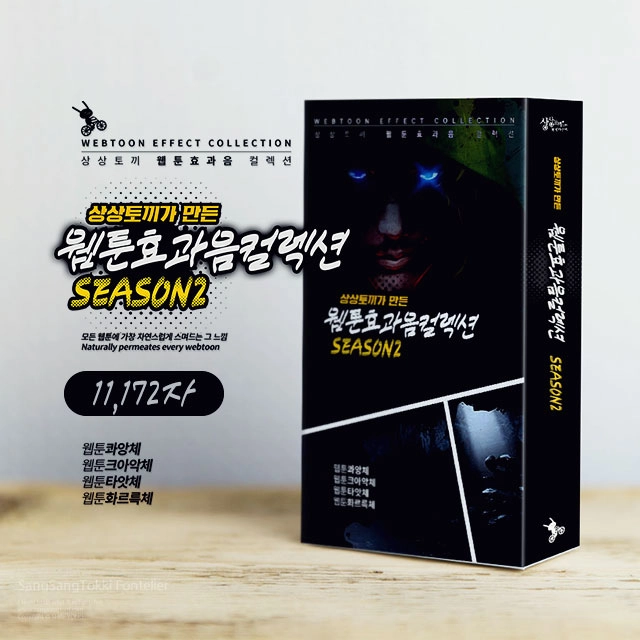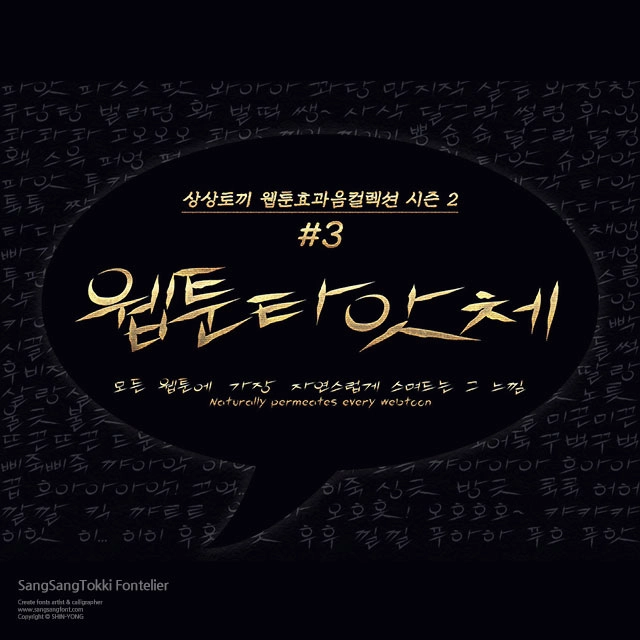
웹툰효과음컬렉션 시즌2, 4종
상상토끼의 웹툰 작가들을 위한 효과음 폰트 패키지 웹툰효과음컬렉션 시즌2, 4종
한글 11,172자 / 영문 52자 / 약물 84자
웹툰콰앙체 1종
웹툰크아악체 1종
웹툰타앗체 1종
웹툰화르륵체 1종
| <웹툰효과음컬렉션>은 웹툰 작가들의 효과음 폰트 선택 고민을 조금이나마 덜어주기 위한 목적으로 기획되었습니다. 효과음 작업시에 상황에 맞는 개성있는 폰트들을 선택하여 사용할 수 있습니다. |
| <웹툰효과음컬렉션> 시즌2는 역동적인 장면 연출에 잘 어울리는 웹툰콰앙체, 좀비물이나 공포/스릴러물에 잘 어울리는 웹툰크아악체, 타격감 있는 액션/느와르물에 찰떡궁합인 웹툰타앗체 그리고 독특한 질감을 가진 웹툰화르륵체까지 총 4종으로 구성되어 있습니다. |
#1 웹툰콰앙체 날카로운 획이 수직으로 길쭉하게 뻗어서 시원한 느낌을 주는 웹툰콰앙체입니다. 임팩트 있는 장면이 많은 스포츠물이나 스피디한 액션물등에 잘 어울립니다.
#2 웹툰크아악체 손으로 막 갈겨 쓴 듯한 거친 획들로 이루어진 웹툰크아악체입니다. 제목에서 알 수 있듯이 비명 소리에 잘 어울리는 폰트로 공포물이나 좀비/스릴러물의 효과음 표현에 좋습니다. 또한, 효과음뿐만이 아니라 거친 대사나 욕설, 소리지르는 문장으로 사용하는데도 불편함이 없습니다.
#3 웹툰타앗체 동작이 크고 역동적인 장면에 어울리는 웹툰콰앙체와 달리 섬세하고 예리한 액션 연출에 좋은 웹툰타앗체입니다. 어둡고 음침한 뒷골목 주먹들의 싸움이나 킬러물/느와르물의 날카로운 액션 연출이 필요할때 선택한다면 더할나위 없이 잘 어울리는 폰트입니다.
#4 웹툰화르륵체 불꽃이 이글거리는 모습을 형상화한 웹툰화르륵체입니다. 웹툰화르륵체는 다른 폰트들과 달리 그 형태가 워낙 명확하기 때문에 사용 범위가 제한적일 수도 있습니다. 하지만 불과 관련한 상황 연출이나 분노로 이글거리는 캐릭터의 감정 묘사등에 잘 활용한다면 멋진 장면을 얻을 수 있을 것입니다.
| <웹툰효과음컬렉션>은 한글 11,172자 / 영문 56자 / 약물 84자를 지원하기 때문에 짧은 단어로 이루어진 웹툰 효과음 뿐만 아니라 일반적인 문장에서도 사용 가능합니다. |
| 또한 조합할 수 있는 모든 경우의 한글을 지원하기 때문에 "똠양꿍"이나 "펲시콜라"와 같은 외래어는 물론 "쀐썀뽉딽" 같이 맞춤법에 어긋난 외계어까지도 표기 가능합니다. |